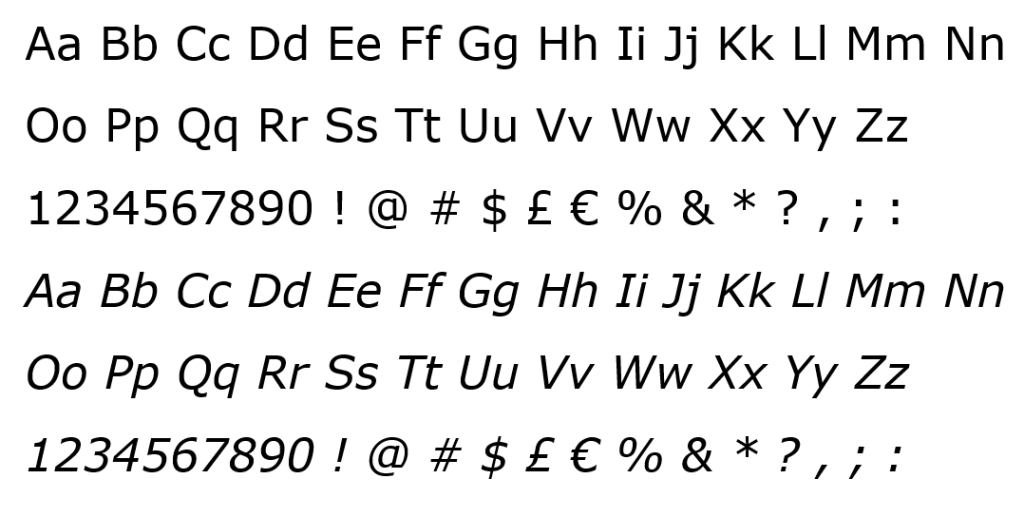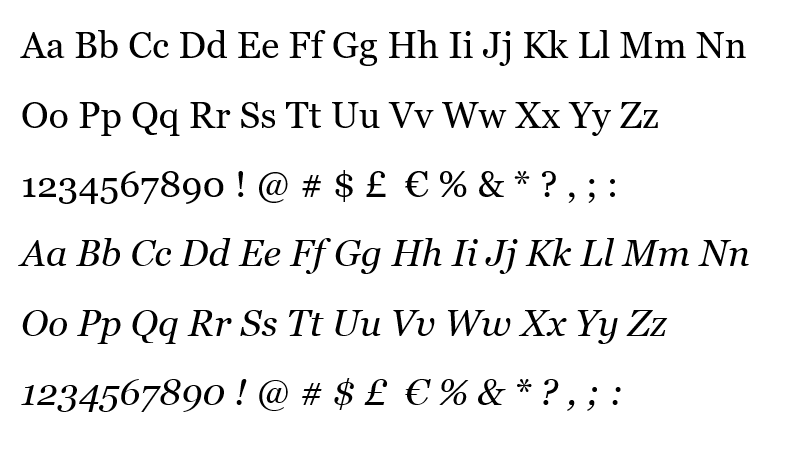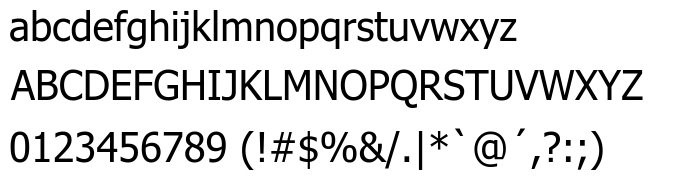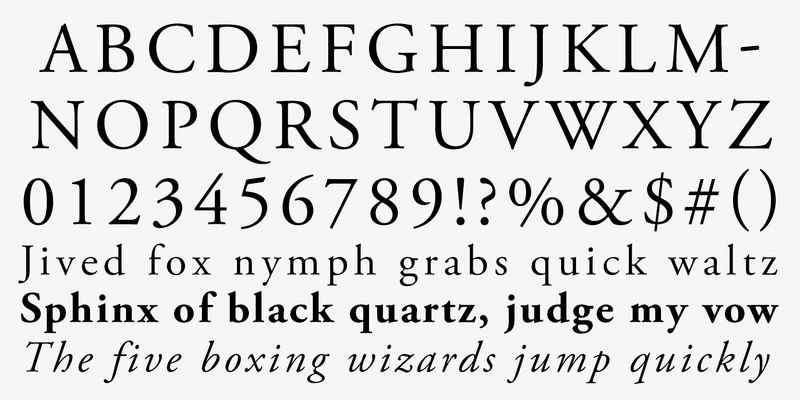
10 Font Chữ Cho Website Đẹp Nhất 2024 Và Những Lưu Ý Chọn Font Chữ
Trong quá trình thiết kế website, ngoài việc xây dựng hình ảnh và bố cục chất lượng, font chữ cũng rất quan trọng. Rất ít người biết rằng cách font chữ ảnh hưởng đến tâm trí người xem.
Do đó, biết cách chọn font chữ phù hợp cho trang web sẽ giúp đảm bảo tính thẩm mỹ của trang web và làm cho nó trở nên chuyên nghiệp hơn và đáng tin cậy hơn đối với chính doanh nghiệp của bạn. Hãy cùng Terus tìm hiểu trong bài viết dưới đây.
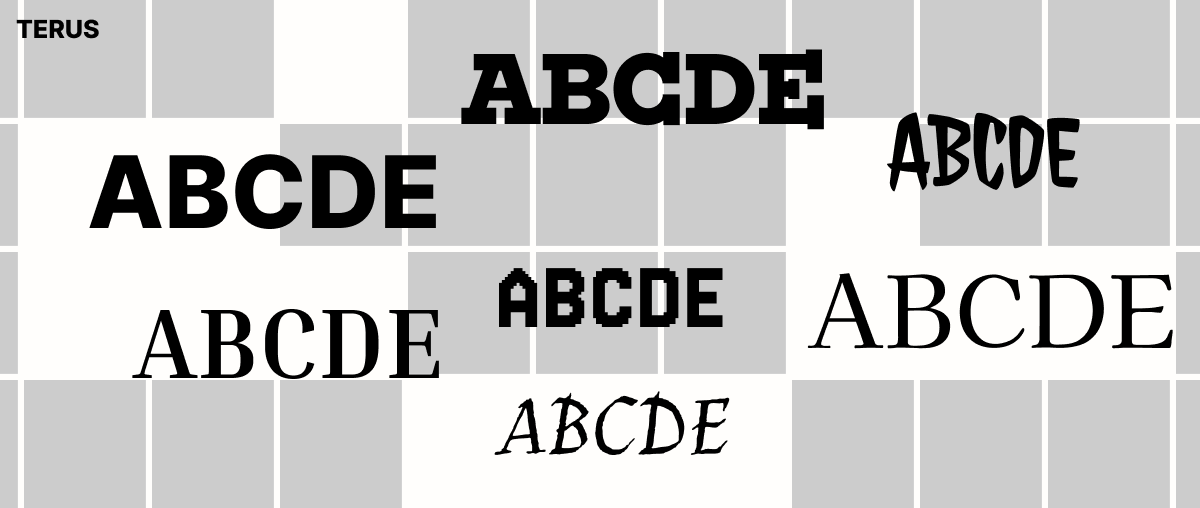
I. Những nguyên tắc cần biết về font chữ khi thiết kế website
Việc lựa chọn font thường diễn ra tùy ý thấy đẹp thì chọn, tuy vậy cũng không có vấn đề gì nhưng cũng cần có một số nguyên tắc giúp bạn đưa ra lựa chọn chuẩn hơn:
1. Sự khác nhau giữa font và typeface
Font bao gồm các chữ cái, dấu câu, số và các ký tự khác có hình dạng, định dạng và kích thước nhất định được gọi là font hoặc phông chữ. Vì vậy, hai loại font khác nhau là Arial và Italic. Nói một cách đơn giản, font chính là một tập hợp các chữ cái thuộc một typeface với các định dạng và hình dạng khác nhau.
Typeface còn được gọi là kiểu chữ là một gia đình của các cá chữ cái có cùng một thiết kế. Một số ký tự bao gồm chữ cái, số, dấu câu, biểu tượng,…
2. Phân loại font
Serif là một loại font có nét gạch ở đầu hoặc dưới dân một số ký tự. Font chữ serif thường được sử dụng trong văn bản phổ thông vì chúng dễ đọc.
Sans serifkhông có nét gạch trên đầu và dưới chân, ngược lại với Serif. Vì nó trông nhỏ gọn, hiện đại và đơn giản nên loại font này thường được sử dụng làm chữ màn hình.
Symbol chữ bao gồm các biểu tượng và ký tự đặc biệt thường được sử dụng để trang trí, minh họa hoặc tượng trưng được gọi là biểu tượng.
Display là các font hiện đại có thiết kế và hình dáng độc đáo được sử dụng để hiển thị. Trang trí, poster, biển quảng cáo,… thường sử dụng loại font này.
Script là phông chữ có dạng như chữ viết tay, thường có nét nối dài và có thể nghiêng. Các mẫu quảng cáo hiện đại thường sử dụng loại font này để tạo hình ảnh với nhiều mục đích.
II. Top 10 font chữ việt hóa đẹp phù hợp với website
Nhiều loại font chữ khác nhau được sử dụng hiện nay. Tuy nhiên, không phải font chữ nào cũng đẹp và việt hóa. Bạn phải dùng font chữ tiếng Việt để đảm bảo nội dung và hình thức của website nếu bạn muốn thiết kế nó phù hợp với ngôn ngữ tiếng Việt.
Terus sẽ đưa ra một danh sách font việt hóa đẹp cho các website được sử dụng phổ biến nhất hiện nay:
Arial
Times New Roman
Helvetica
Courier
Verdana
Georgia
Tahoma
Calibri
Garamond
Bookman
1. Arial
Arial là font web phổ biến nhất hiện nay vì nó đơn giản và dễ nhìn. Loại font trong nhóm Sans Serif phổ biến nhất là Arial, có thể sử dụng thay thế cho nhiều loại font khác trong hệ điều hành Windows.
Arial là “phông chữ kiểu sans-serif được gói với vài phần mềm ứng dụng của Microsoft. Nó được phát triển năm 1982 bởi Robin Nicholas và Patricia Saunders cho Monotype Typography là phông rẻ để thay cho phông Helvetica phổ biến của Linotype” – Theo Wikipedia.
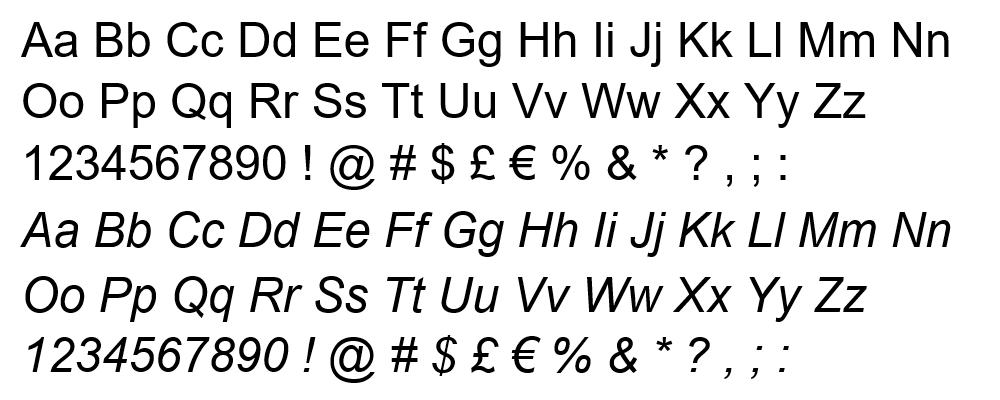
2. Times New Roman
Times New Roman là “phông chữ kiểu serif được nhật báo The Times (Luân Đôn) ủy thác Stanley Morison thiết kế năm 1931 cùng với Starling Burgess và Victor Lardent. Nó được phát hành lần đầu tiên bởi Công ty Monotype năm 1932. Tuy The Times không còn sử dụng nó, nhưng nó vẫn được sử dụng rộng rãi trong cuốn sách.” – Theo Wikipedia
Bởi vì nó rất phổ biến trong việc soạn thảo văn bản hiện nay, có thể coi đây là font chữ “quốc dân”. Trong Windows, Times New Roman gần như là font mặc định và phù hợp với các trang báo chí và nội dung tài liệu.
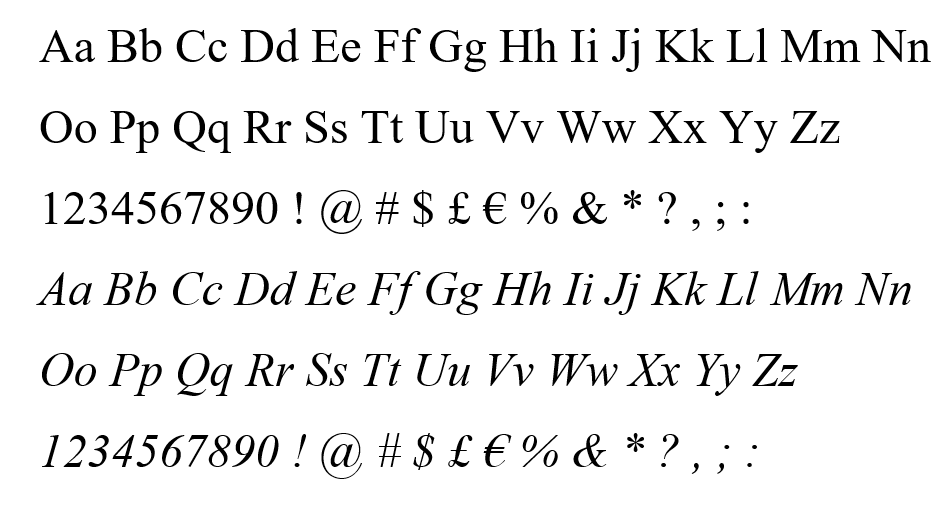
3. Helvetica
Font Helvetica được tạo ra vào cuối những năm 1950 nhờ sự hợp tác giữa hai nhà thiết kế font chữ người Thụy Sĩ là Max Miedinger và Eduard Hoffmann.
Trong lĩnh vực đồ họa và thiết kế, font chữ rất quan trọng để truyền đạt thông điệp và tạo nên phong cách của một sản phẩm. Helvetica là một trong những font chữ phổ biến nhất và được sử dụng nhiều nhất trong lĩnh vực này. Font sans-serif không có gạch chân Helvetica có thiết kế đơn giản và dễ đọc. Nó đã trở thành một biểu tượng trong thiết kế của sự thời thượng và sự tối giản.
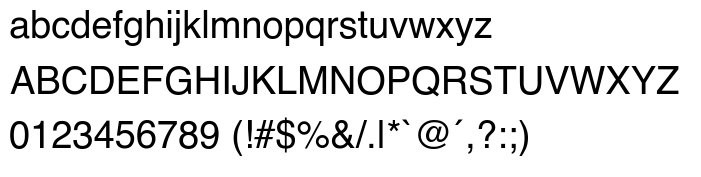
Helvetica, một loại font Sans Serif, có chiều cao và khoảng cách giữa hai ký tự gần giống nhau. Helvetica là font tốt cho chữ nhỏ và dễ đọc với người dùng.
4. Courier
Courier là một kiểu chữ có chân dạng phiến đơn cách. Courier được IBM tạo ra vào giữa những năm 1950 và được thiết kế bởi Howard “Bud” Kettler (1919–1999). Font Courier và khái niệm kiểu chữ đều thuộc phạm vi công cộng. Courier đã được điều chỉnh để sử dụng làm phông chữ máy tính và các phiên bản của nó được cài đặt trên hầu hết các máy tính để bàn.
Courier new và Times New Roman là font chữ quen thuộc với những người thường xuyên sử dụng trình soạn thảo. Hiện nay, font Courier mới được coi là lựa chọn tốt nhất để viết nội dung.